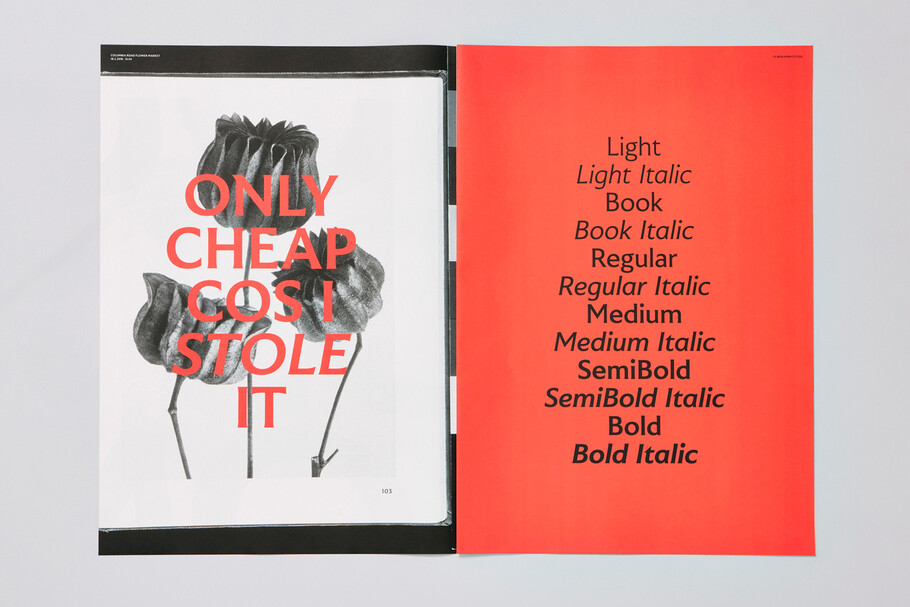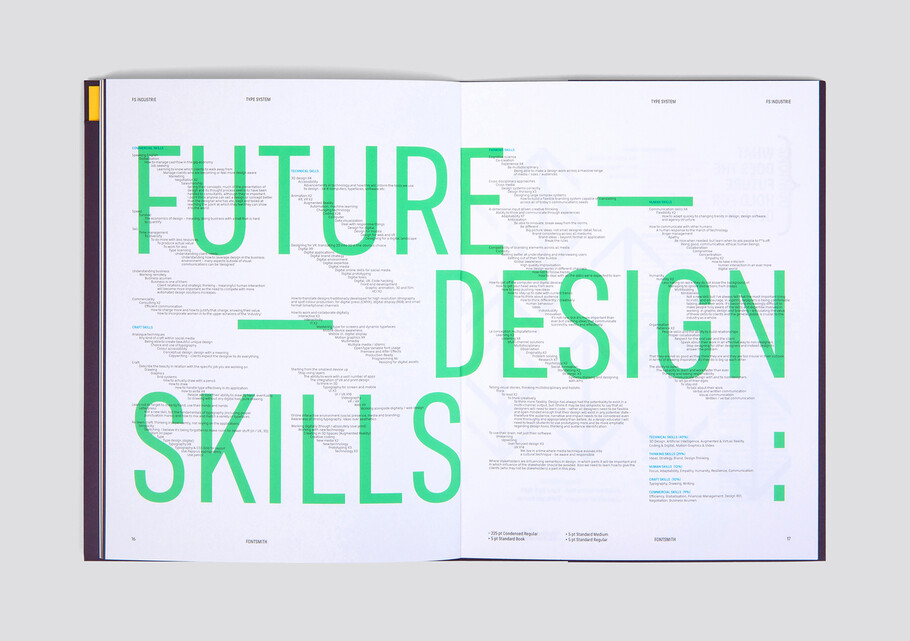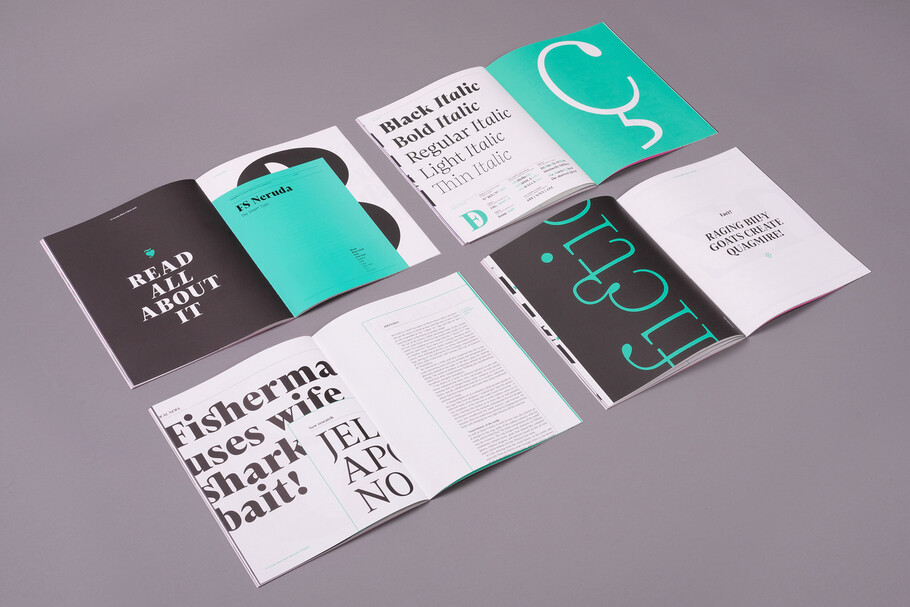
Fontsmith rejoint la bibliothèque de Monotype
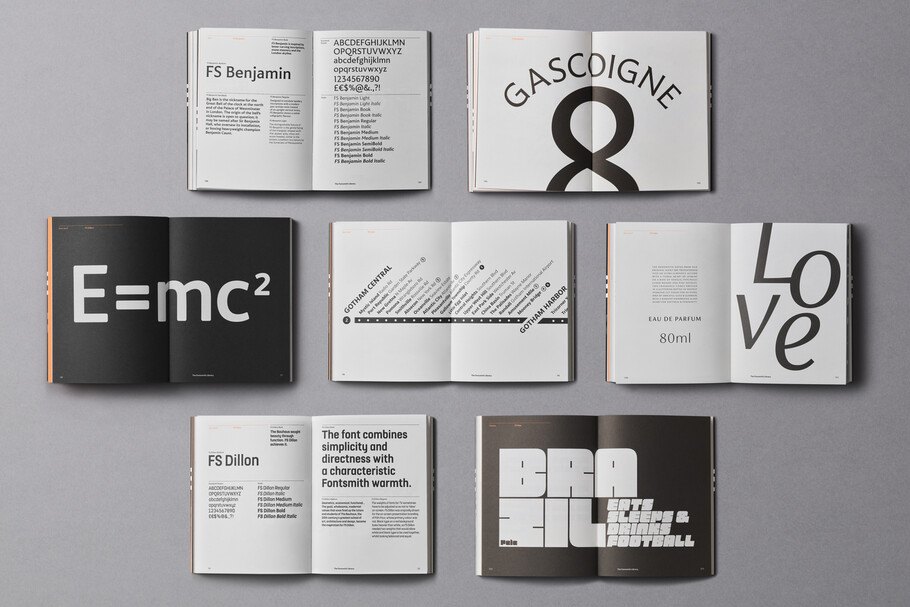
Jason Smith, fondateur de Fontsmith
Demandez-lui ce que les clients de Monotype Fonts doivent penser de l’arrivée de sa fonderie dans leur bibliothèque, et le fondateur de Fontsmith, Jason Smith, devient particulièrement éloquent.
« Je pense que les clients de Monotype Fonts devraient être très enthousiastes », dit-il. « Nous allons apporter à la bibliothèque quelque chose d’assez cool et expressif. »
Smith a de bonnes raisons d’avoir l’air si confiant. Depuis sa création en 1997, Fontsmith a acquis la réputation de créer des polices de caractères audacieuses, uniques et à la pointe de la mode, pour lesquelles il a reçu de nombreux prix et distinctions. C’est la première fois que la bibliothèque de Fontsmith est disponible en dehors du site de la fonderie de lui-même.
Aujourd’hui, ces années d’expérience et d’expertise ainsi que ces polices de caractères font partie de la bibliothèque Monotype et sont disponibles avec des droits illimités sur les ordinateurs de bureau pour tous les clients de la plateforme. Cela signifie l’accès à quarante-huit nouvelles familles de polices totalisant environ six cents polices individuelles, notamment des designs récompensés tels que FS Albert, FS Brabo, FS Emeric, FS Millbank et FS Neruda.
En plus des familles désormais disponibles dans Monotype Fonts, Fontsmith apporte une nouvelle profondeur aux services de polices personnalisées offerts par Monotype. La fonderie compte une impressionnante collection de travaux et logos personnalisés pour certaines des plus grandes marques mondiales, dont la BBC, Colgate, ING, Lloyds Bank, Renault, Sky et Xerox. Cette expertise est désormais mise à la disposition des clients de la typothèque, étoffant le portfolio des polices personnalisées que Monotype a créé pour un large éventail de secteurs et de marques mondiales, dont Alibaba, H&M, Santander, Toyota, et d’innombrables autres.
« J’ai été impressionné à la fois par la qualité de leur travail et par le calibre de leur clientèle », déclare Tom Rickner, directeur de la création typographique chez Monotype. « Nous avons déjà été en concurrence avec eux dans le passé pour des travaux personnalisés et je suis enthousiaste de les voir rejoindre la remarquable équipe de designers que nous avons aujourd’hui ».
Ce moment a une signification importante pour Fontsmith. « C’est presque comme si nous avions enfin atteint notre but », explique Phil Garnham, directeur de la création typographique senior. « Ce n’est peut-être pas la vérité, mais on a le sentiment d’être légitime, comme si nous avions fait nos preuves dans le secteur. Et maintenant, nous avons la possibilité de poursuivre ce que nous avons entrepris et de nous développer. »
« Monotype m’a semblé être l’endroit où je pourrais faire connaître mon travail à un public plus large à travers le monde entier, en particulier avec Monotype Fonts », ajoute Smith. « Il est très difficile pour une petite entreprise d’accéder au niveau mondial et aux marques directement, et avec Monotype, cela va être beaucoup plus facile », explique Smith. « Nous sommes très actifs à Londres et nous avons plusieurs clients aux États-Unis et en Europe, mais le fait de faire partie de Monotype signifie que notre champ d’action devient beaucoup plus vaste. »
Bien plus qu’une simple arrivée, il s’agit en réalité d’un partenariat fondé sur une admiration mutuelle et un sens partagé des opportunités. « Avec le temps, il semble que Monotype et Fontsmith aient commencé à faire les choses et à commercialiser les polices de la même manière, à parler aux mêmes clients », explique Garnham. « Tout cela se croisait, et nous avons commencé à penser qu’il serait peut-être mieux de s’associer. »
« Même le bureau de Monotype à Londres se trouvait juste en face du nôtre. Je vous assure, à seulement cinq mètres ! Nous levions les yeux et nous voyions [le designer typographique senior Toshi Omigari] juste derrière la fenêtre. »
Pedro Arilla, directeur de la création typographique, arrivé chez Fontsmith trois ans plus tôt, a rapidement réalisé qu’il y avait une sorte d’énergie particulière dans le studio. Il pense que l’équipe de Fontsmith peut apporter quelque chose d’original et d’enthousiaste à Monotype, une complémentarité à son histoire et à sa stature.
Jason Smith, fondateur de Fontsmith.
« C’est excitant pour nous de faire partie de la fonderie la plus ancienne du monde et c’est inspirant de pouvoir maintenant contribuer à cette riche histoire. C’est aussi un défi passionnant de réfléchir à la manière dont nous pouvons avancer avec eux sur ce chemin », dit-il. « Tout le monde sait que Monotype possède une superbe bibliothèque avec certains des meilleurs caractères jamais réalisés, donc y contribuer est un immense honneur ».
« Je crois que Fontsmith apporte de la nouveauté à l’approche créative », ajoute Garnham. « Nous faisons les choses de manière légèrement décalée, dans un esprit intentionnellement provocateur. Nous aimons tout simplement dessiner des caractères, et si nous enfreignons quelques «règles», c’est très bien. Je pense donc que nous allons apporter une certaine volonté d’essayer des choses et d’expérimenter. À quoi bon faire quelque chose si ce n’est pas pour créer quelque chose de nouveau ? »
« Il y a un respect mutuel important entre Fontsmith et Monotype », déclare Smith. « Je suis reconnaissant que Monotype se soit intéressé à nous. »
En riant, il ajoute : « Et Monotype est reconnaissant que nous nous soyons intéressés à eux ».